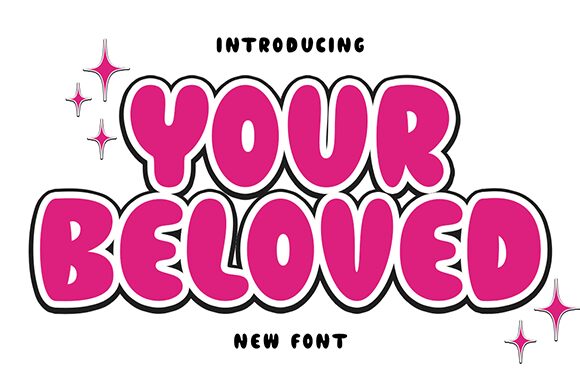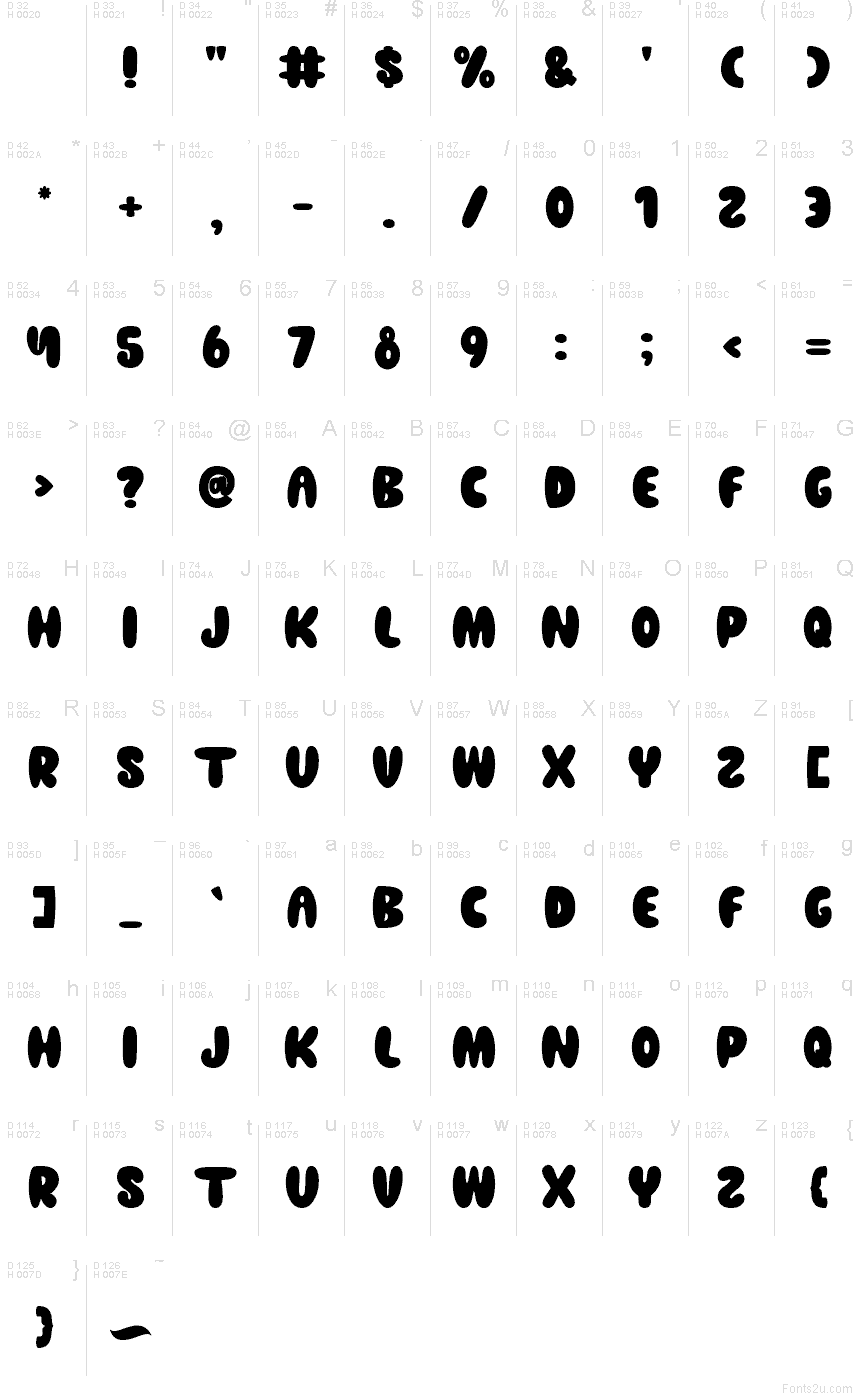
Písmo Your Beloved od Wahyu Setiyawana z Wahyu Studio je bezplatný font ve stylu cartoon s baculatými, skákavými písmeny, která působí jako měkké bonbony marshmallow namočené v čerstvém inkoustu. Robustní tvary a zaoblené hrany dodávají písmu přátelský a výrazný charakter, aniž by působilo nečitelně – vaše slova budou snadno čitelná, i když je zvětšíte. Má v sobě tu hravou energii „krabice s hračkami“, díky které se nadpisy rozzáří na první pohled.
S Your Beloved získáte působivé výsledky na dětských plakátech, obalech na svačinu, arších samolepek, náhledech videí na YouTube, hravých logách, pozvánkách na oslavy či školních materiálech. Tento bezplatný font vynikne také na merchi, jako jsou trička nebo plátěné tašky, pokud zvolíte krátký a úderný text. V hlavním textu jej kombinujte s čistým geometrickým bezpatkovým písmem a ponechte velkorysé rozestupy, aby jeho bublinkový rytmus mohl volně dýchat.